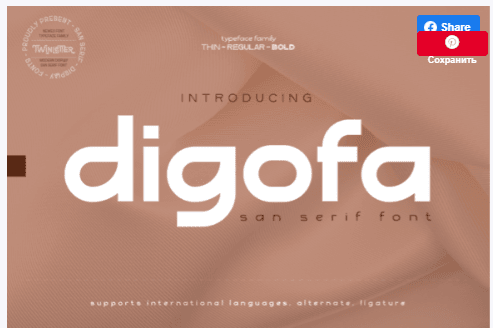
Digofa Font
Digofa - это классный и аккуратный шрифт без засечек. Этот шрифт идеально подходит для написания веб-дизайнов, визиток и всего остального, что требует уникального подхода.